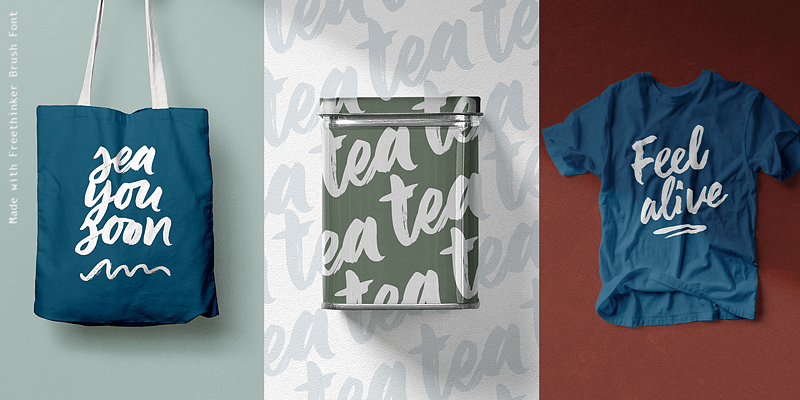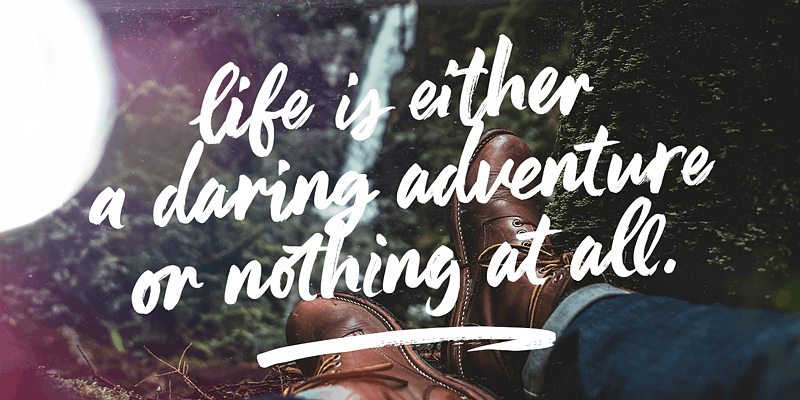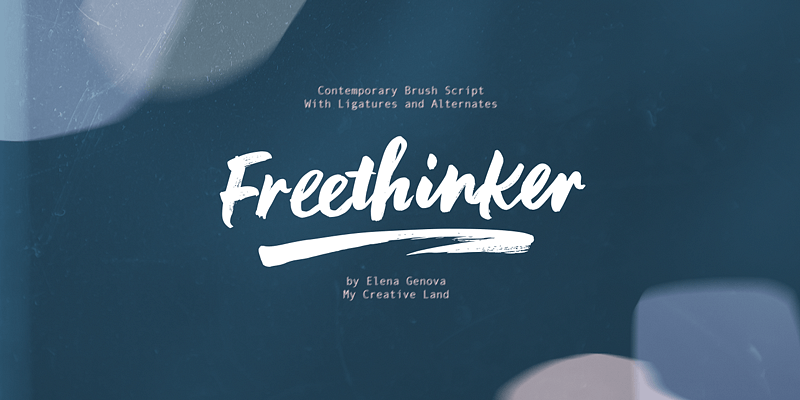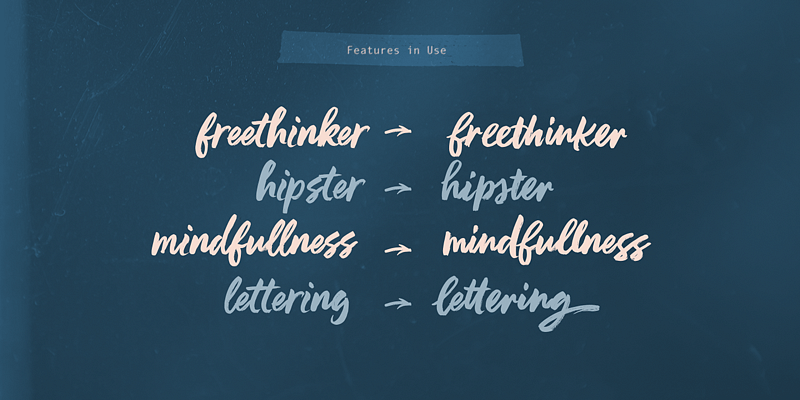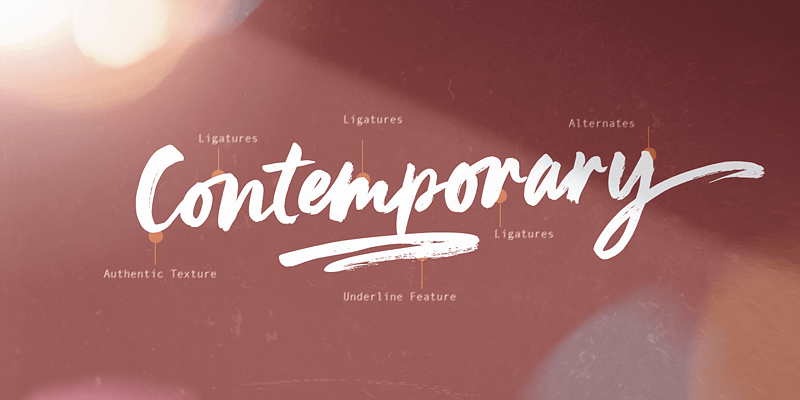
My Creative Land는 Elena Genova가 손으로 직접 만든 멋진 서체를 제작합니다. 서체 예술에 대한 확고한 헌신으로 디자인된 서체들은 평범함을 초월하고 디자인의 감정, 깊이 및 독창성을 전달합니다. 각 제품군은 세심하게 손수 제작되으며 캘리그래피와 레터링에서 발견하는 아름다움에서 직접적인 영감을 얻습니다. 안목 있는 디자이너라면 My Creative Land의 글꼴은 특정 je ne sais quoi를 불어넣어 다른 것들보다 자신의 아이디어를 증폭시킬 수 있다는 것을 확인할 수 있을 것입니다.